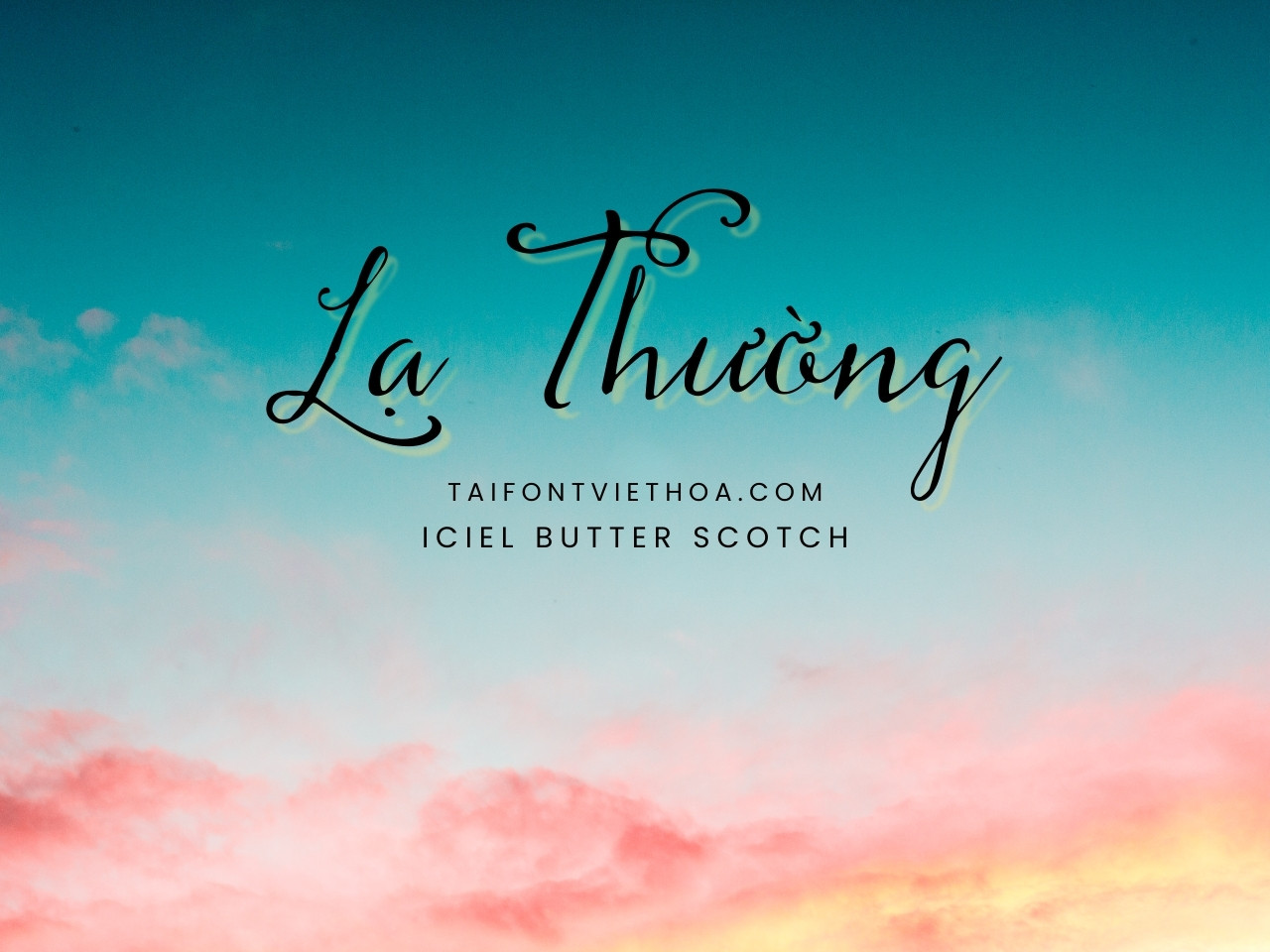
Giới thiệu về font iCiel Butterscotch – Ngọt ngào, dễ thương và đậm chất thủ công
iCiel Butterscotch là một font chữ viết tay (handwritten script) mang phong cách vui nhộn, ngọt ngào và thủ công. Font được thiết kế với các đường nét phóng khoáng, tròn trịa và mang lại cảm giác thân thiện như một lời viết tay đầy tình cảm. Phiên bản Việt hóa được thực hiện bởi iCiel, hỗ trợ đầy đủ tiếng Việt và hơn 60 ngôn ngữ khác, giúp font dễ dàng sử dụng trong các dự án quốc tế hoặc thiết kế cá nhân hóa.
Font đã được taifontviethoa.com chọn lọc và sưu tầm kỹ lưỡng, đặc biệt phù hợp cho các dự án sáng tạo dành cho trẻ em, thực phẩm, sản phẩm thủ công hoặc các thiết kế truyền cảm hứng. Với vẻ ngoài đáng yêu, tự nhiên và mang đậm hơi thở lễ hội, iCiel Butterscotch là lựa chọn lý tưởng để truyền tải sự vui tươi, thân mật và chân thành qua từng dòng chữ.
Đặc điểm thiết kế và ứng dụng nổi bật của font iCiel Butterscotch
Font Butterscotch nổi bật với nét viết tay mềm mại, đều đặn và tròn đầy. Các ký tự được thiết kế linh hoạt với các nét nối ngẫu hứng, mang đến cảm giác như được vẽ bằng tay thực sự. Từng đường cong, nét uốn tạo nên vẻ bay bổng và dễ đọc, đồng thời giúp tăng tính sinh động cho tổng thể thiết kế. Font còn hỗ trợ các ligature cơ bản, phù hợp với trình bày chữ nghệ thuật và tên thương hiệu cá nhân.
iCiel Butterscotch phù hợp với các ngành nghề như thực phẩm, bánh kẹo, spa, sản phẩm handmade, thời trang trẻ em, mỹ phẩm thiên nhiên hoặc các chiến dịch truyền thông mang tính lễ hội. Các ứng dụng tiêu biểu gồm: thiết kế bao bì kẹo – bánh, poster sinh nhật, thiệp mời Trung thu, typography quote dễ thương, bìa sách thiếu nhi hoặc thiết kế fanpage bán hàng thủ công, sáng tạo.